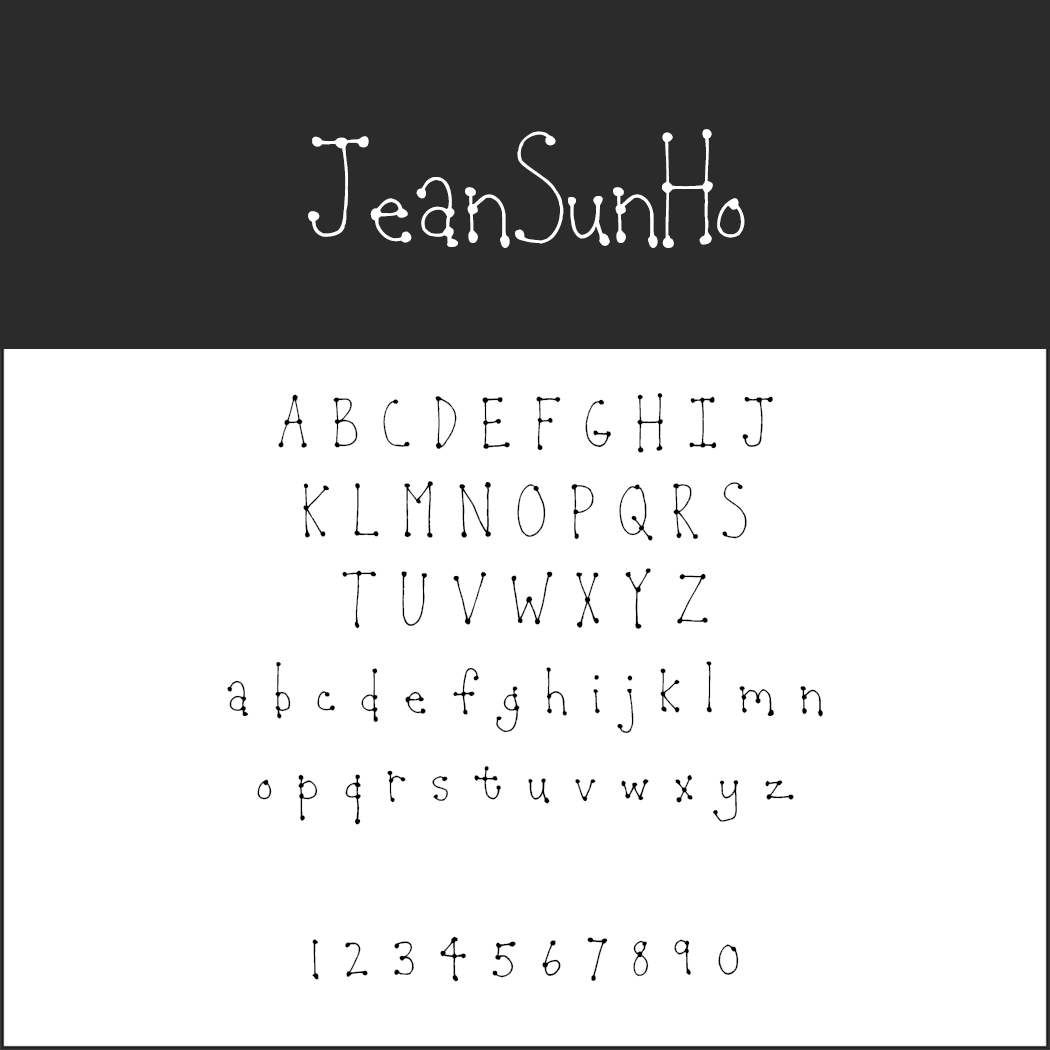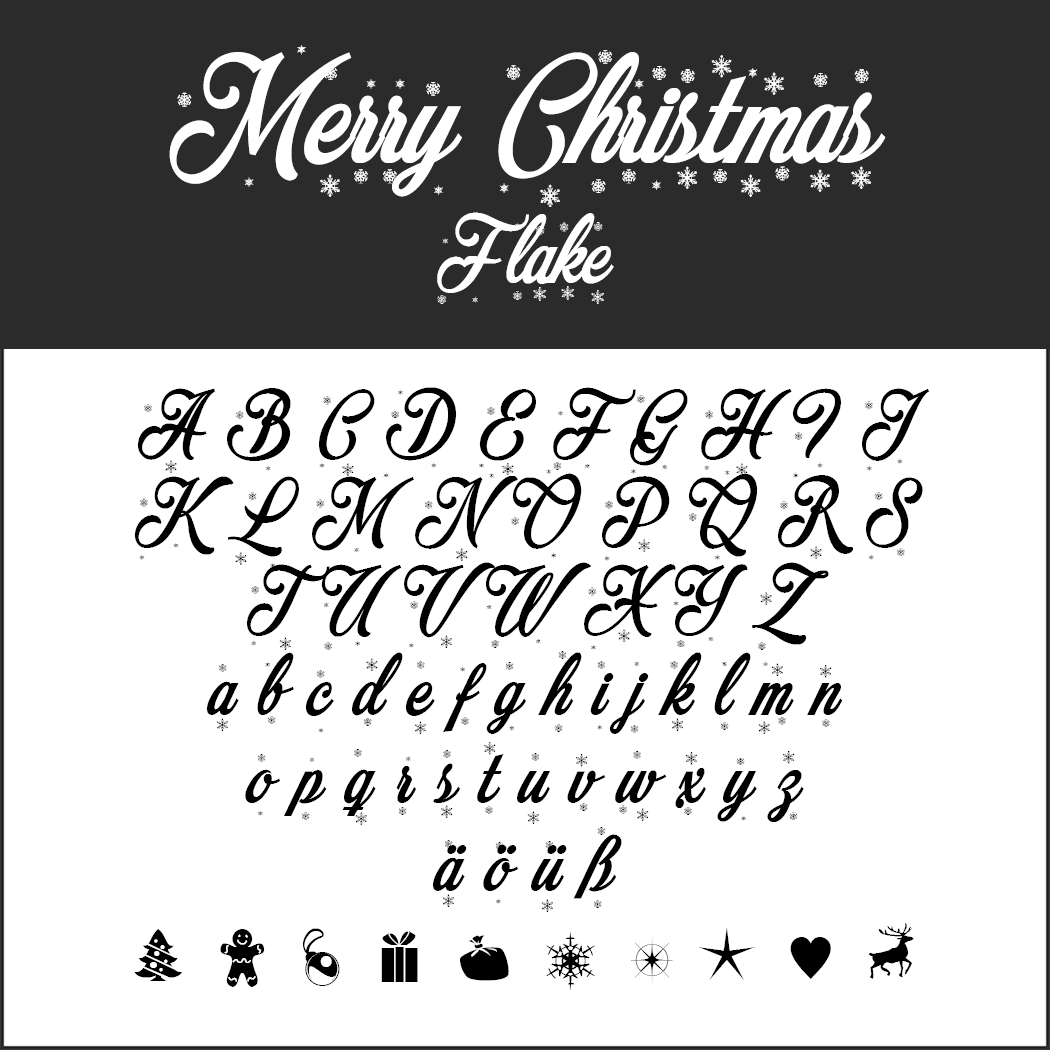
Von klassisch bis kitschig: Die Auswahl an Christmas Fonts ist riesig. Jedoch sind nicht alle Schriftarten ohne Weiteres download- und nutzbar. Wichtig sind die jeweiligen Lizenzbestimmungen. Ob zur Gestaltung von weihnachtlichen Grußkarten für Kunden und Geschäftspartner oder zum Erstellen hübscher Geschenkanhänger für Familienmitglieder: in dieser Font-Sammlung finden Sie sowohl kommerziell als auch außschließlich privat nutzbare Christmas Fonts. Dabei stehen Ihnen alle nachfolgenden Fonts auf den jeweiligen Plattformen kostenlos zum Download zur Verfügung.
Christmas Fonts zur kommerziellen Nutzung
Christmas Fonts für den privaten Gebrauch
Christmas Fonts – frei zur kommerziellen Nutzung
Christmas Fonts _ Wintersoul
Wintersoul
Die Schreibschrift-Schriftart sieht wie mit dem Pinsel und von Hand gemalt aus. Das verleiht ihr eine persönliche Note. Die breiten Pinselstriche erinnern an dicke Schneeschichten und schaffen so eine Illusion vom „Winter Wonderland“. Die Umlaute sind in dem Paket nicht enthalten.
• Design by: Garisman Studio
Christmas Fonts _ Font Chopin Script
Chopin Script
Dieser Christmas Font wirkt edel und verspielt. Er sieht aus wie von einem Weihnachtsengel mit der Feder zu Papier gebracht und eignet sich zum Beispiel gut für klassische Menükarten zum Weihnachtsessen oder Plakate zur Ankündigung des nächsten Weihnachtskonzerts.
• Besonderheiten: Diakritsche Zeichen enthalten
• Design by: Diogene
Christmas Fonts: Jandles
Jandles
Die Schriftart Jandles zeichnet sich durch ihre vielen Kringel aus. Sie erinnert an Spritzgebäck und passt deshalb ideal zu Weihnachten.
• Besonderheiten: Diakritsche Zeichen enthalten
• Design by: Raymond Larabie
Christmas Fonts: Jeansunho
JeanSunHo Font Family
Dieser verspielte Christmas Font sieht mit seinen integrierten Punkten lustig aus. Grußkarten, Dankeskarten oder Einladungskarten wirken, als wären sie von den Weihnachtselfen selbst geschrieben worden.
• Design by: Kevin Richey
Christmas Fonts: Christmas Sounds
Christmas Sounds
Die Versalien – also die Großbuchstaben – sowie die Zahlen dieses Christmas Fonts sind mit kleinen, für die Weihnachts- und Winterzeit typischen Ornamenten geschmückt. Die Schriftart eignet sich deshalb sehr gut für Überschriften oder einzelne Wörter, wobei reine Versal-Überschriften besonders auffallen.
• Design by: Tipografia Leone
Christmas Fonts: Rudiment
Rudiment
Der serifenlose Christmas Font ist simple und dennoch schön. Je größer die dünne Schrift zum Einsatz kommt, desto besser ist ihre Kreide-Struktur zu erkennen.
• Design by: Kevin Richey
Christmas Fonts: Candy Stripe
Candy Stripe
Der Font erinnert an die Candy Canes bzw. Zuckerspazierstöcke – also die typisch rot-weiß gestreiften Süßigkeiten, welche vor allem in den USA an Weihnachten allgegenwärtig sind.
• Design by: Ænigma Fonts
Christmas Fonts – frei für die private Nutzung
Christmas Fonts: Christmas on Crack
Christmas On Crack
Etwas weniger festlich und weihnachtlich romantisch als andere Christmas Fonts, kommt diese Schriftart daher. Sie wirkt abgehakt und etwas wackelig, gleichzeitig aber auch verspielt, da viele Buchstaben mit kleinen Kringeln versehen sind.
• Besonderheiten: Zahlen und gängige Satzzeichen enthalten
• Design by: Parallax
Christmas Fonts: Frosty
Frosty
Bei dieser Schriftart wird einem gleich etwas kälter ums Herz. Die Ausführung der Buchstaben ist etwas schief, was an schneebedeckte Dächer oder sogar nahende Schneelawinen erinnert. Die Gemeine – also die Kleinbuchstaben – sind von Schneeflocken umgeben und das Font-Set beinhaltet eine große Anzahl an weiteren verschiedenen Schneeflocken und Schneeflöckchen.
• Besonderheiten: Der Künstler redesignt bekannte Schriftzüge aus Filmen und stellt sie für die private, nicht-kommerzielle Nutzung kostenfrei zum Download.
• Design by: FZ (Franco Fernández)